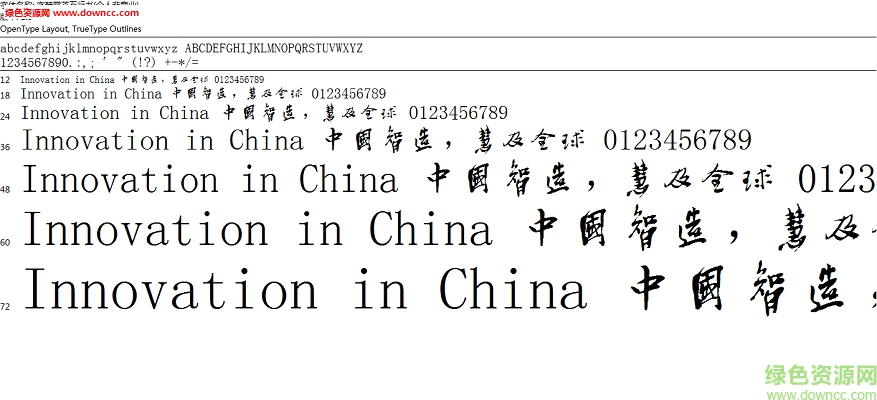
軟件介紹 軟件標簽: 字酷堂 字酷堂蒼石行書體是由字酷堂推出的一款行書字體,字體看似略顯窄小,可細品之下,卻能看出其渾厚之處,讓你越看越舒服,喜歡這款字體的朋友們快來綠色資源網下載吧!相關介紹:字酷堂字體制作的底稿多是采用掃描近代書法家的字帖和字跡制作而成,故書法味道挺濃(也正因為此,所以目前字酷堂字體多為繁體字庫,簡入繁出(輸入簡體字直接顯示為繁體))適合用于海報設計、banner設計、包裝設計、古籍排版、網頁設計等方面。相關推薦:字酷堂鄭板橋行書體 免費版授權:免費軟件 WinAll大?。?.1M語言:中文字酷堂鄭板橋行書體高度還原了鄭板橋的行書字體,字體極具藝術風格,每筆每畫都給人一種飄逸灑脫的感覺,而在飄逸之余不失大氣,更顯難得,感興趣的朋友們快來下載吧!字體介紹:字酷堂鄭板橋行書體是一種應用于設下載地址安裝說明:如果您是Win7用戶直接右鍵選擇安裝即可,其他系統(tǒng)的用戶可以將字體文件復制到C:\Windows\Fonts文件夾即可完成安裝 軟件截圖 上一張下一張(1 / 1) 安裝詳細截圖 猜你喜歡 行書字體 字酷堂字體 行書字體 行書字體包括了鋼筆字行書字體大全、硬筆行書字體等,是一種介于楷書和草書之間的字體。為什么這樣說?因為行書字體既有草書的流暢感,又有楷書的端正感,可以說,行書結合了草書和楷書的特點,形成了獨特好看的行書字體。喜歡的朋友,趕快下載體驗吧! 查看更多>> 繁體行書字體 9.76M/中文/4.0/免費版下載 winman tun10011字體 17.57M/中文/6.6/下載 南構嘉飛行書字體 10.00M/中文/6.6/下載 c g流麗行書體繁/簡 4.39M/中文/5.0/下載 北方行書簡體 2.63M/中文/7.2/下載 qxyingbixing 1.26M/中文/8.0/下載 字酷堂字體 字酷堂是一個專門致力于書法字體開發(fā)的網站,字酷堂系列字體都是脫胎于書法字體,字體多為繁體字庫,簡入繁出(輸入簡體字直接顯示為繁體),十分適合用于海報設計、古籍排版、包裝設計、banner設計、網頁設計等方面。是一款非常不錯的字體類型,喜歡這一系列字體的朋友們千萬不要錯過哦! 查看更多>> zktqkt 5.52M/中文/5.0/下載 字酷堂黃楷體字體 10.00M/中文/5.0/下載 漢儀字酷堂義山楷字體 10.00M/中文/3.3/下載 zikutangsfxst 2.44M/中文/10.0/下載 zikutanghzkt字體 2.44M/中文/10.0/下載 字酷堂南元松雪行書字體 182.20M/中文/0.9/下載 其他版本下載 標題 大小 更新日期 下載 下載地址 電腦版 字酷堂蒼石行書體 免費版 點擊報錯 軟件無法下載或下載后無法使用,請點擊報錯,謝謝! 關閉報錯反饋 請描述您所遇到的錯誤,我們將盡快予以修正,謝謝! *必填項,請輸入內容 本類最新 首爾南山體字體 v1.06 官方版 潮字社風云簡ttf 潮字社凌渡鯤鵬簡體字體 潮字社曾玉波手書簡字體 微博慧心字體 阿里巴巴iconfont字體庫 用戶評論 熱門評論 最新評論 發(fā)表評論 查看所有評論(0) 昵稱: 請不要評論無意義或臟話,我們所有評論會有人工審核. 字數(shù): 0/500 (您的評論需要經過審核才能顯示)